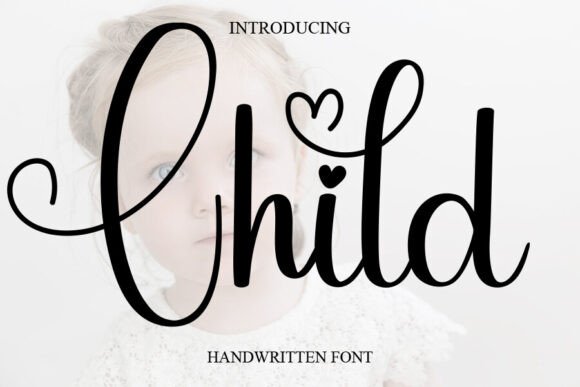
Child
**Polices de caractères pour enfants : La magnifique Child**
Si vous cherchez un polices de caractères qui capture l'essence de la simplicité et de la beauté, alors la Child est faite pour vous. Cette magnifique police de caractères manuscrite est conçue pour créer des logos, des marques et des citations qui font désirer le monde.
### Caractéristiques de la Child
- **Unique et belle** : Chaque lettre de la Child a un touché unique et beau qui la fait ressembler à une oeuvre d'art.
- **Temporelle** : La Child est une police de caractères temporelle, ce qui signifie qu'elle garde son charme pendant les années.
- **Polyvalente** : La Child est idéale pour créer des logos, des marques, des citations et bien plus encore.
### Comment utiliser la Child
- **Créer des logos** : La Child est parfaite pour créer des logos qui font impression et qui sont mémorables.
- **Branding** : Utilisez la Child pour créer des marques qui reflètent votre personnalité et votre style.
- **Citations** : La Child est idéale pour créer des citations qui sont belles et qui font émouvoir.
### Conclusions
La Child est une police de caractères qui a beaucoup à offrir. Avec son touché unique et beau, elle est parfaite pour créer des designs qui font émouvoir. Si vous cherchez une police de caractères qui est temporelle et qui est polyvalente, alors la Child est faite pour vous.
#### Les avantages de la Child
- Unique et belle
- Temporelle
- Polyvalente
- Idéale pour créer des logos et des marques
#### Les inconvénients de la Child
- Pas idéal pour les polices de caractères modernes